我们处在一个全民娱乐时代,连字也不只是像以前一样端端正正,变得有趣起来,有了娱乐化的一面,一般像明星签名都用的艺术字体,一改以往的“端庄”。综艺的热门发展带火了综艺字体,在许多社交软件的字体库也出现了各种各样的综艺字体。
综艺字体最初是综艺节目中用来增添节目效果而用的字体,它不仅能将节目内容表达出来,而且还能带动气氛,例如义启紫水晶体就经常被用于综艺节目中,于是被综艺节目广泛使用。随着技术的发展,人们思想包容度的扩大,综艺字体后来慢慢延伸到了普通百姓的生活中,成为了人们在日常生活中使用频率很高的社交字体,因为综艺字体可以展示个人的性格,还能愉快聊天氛围,因此广受欢迎。
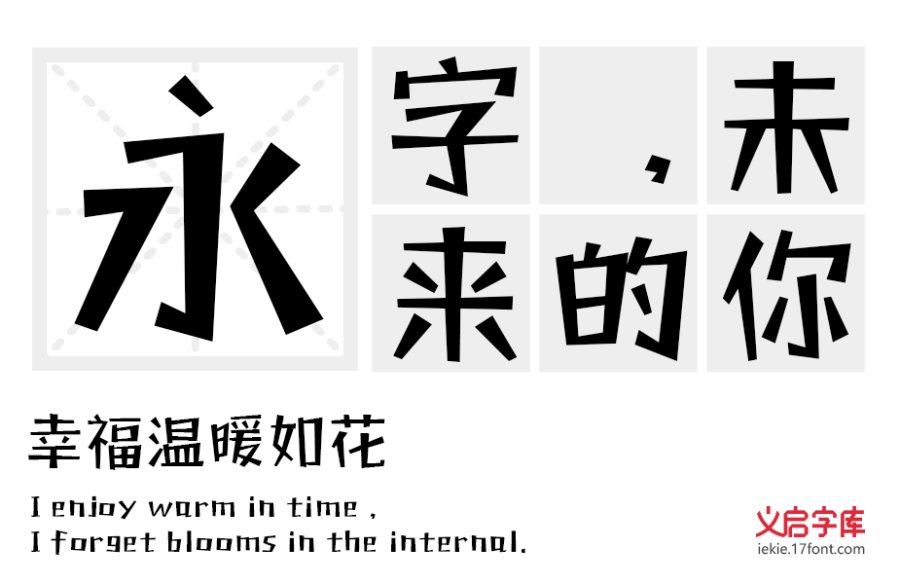
综艺字体这么受欢迎,就有许多人去特地练习综艺字体,因为对于我们普通老百姓来说综艺字体不仅仅只是用于社交聊天中,我们可以学习练习综艺字体来进行平面设计、广告设计等。综艺字体的练习不像传统的楷体、行书等书法的练习,传统书法的练习可以报字体练习班,买字帖练习,而综艺字体的练习没有这么方便,建议想要练习综艺字体的小伙伴们可以通过下载字体库来学习。